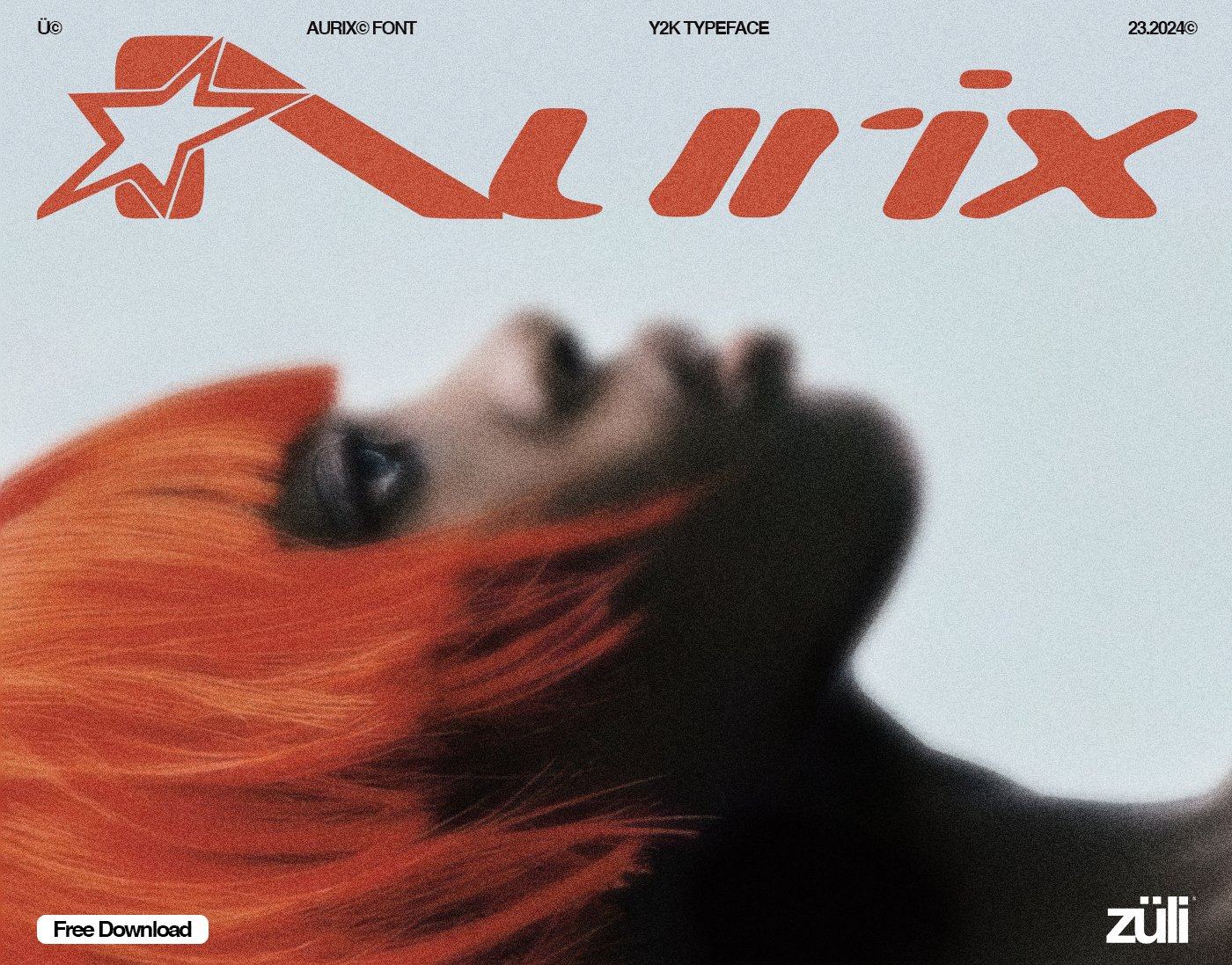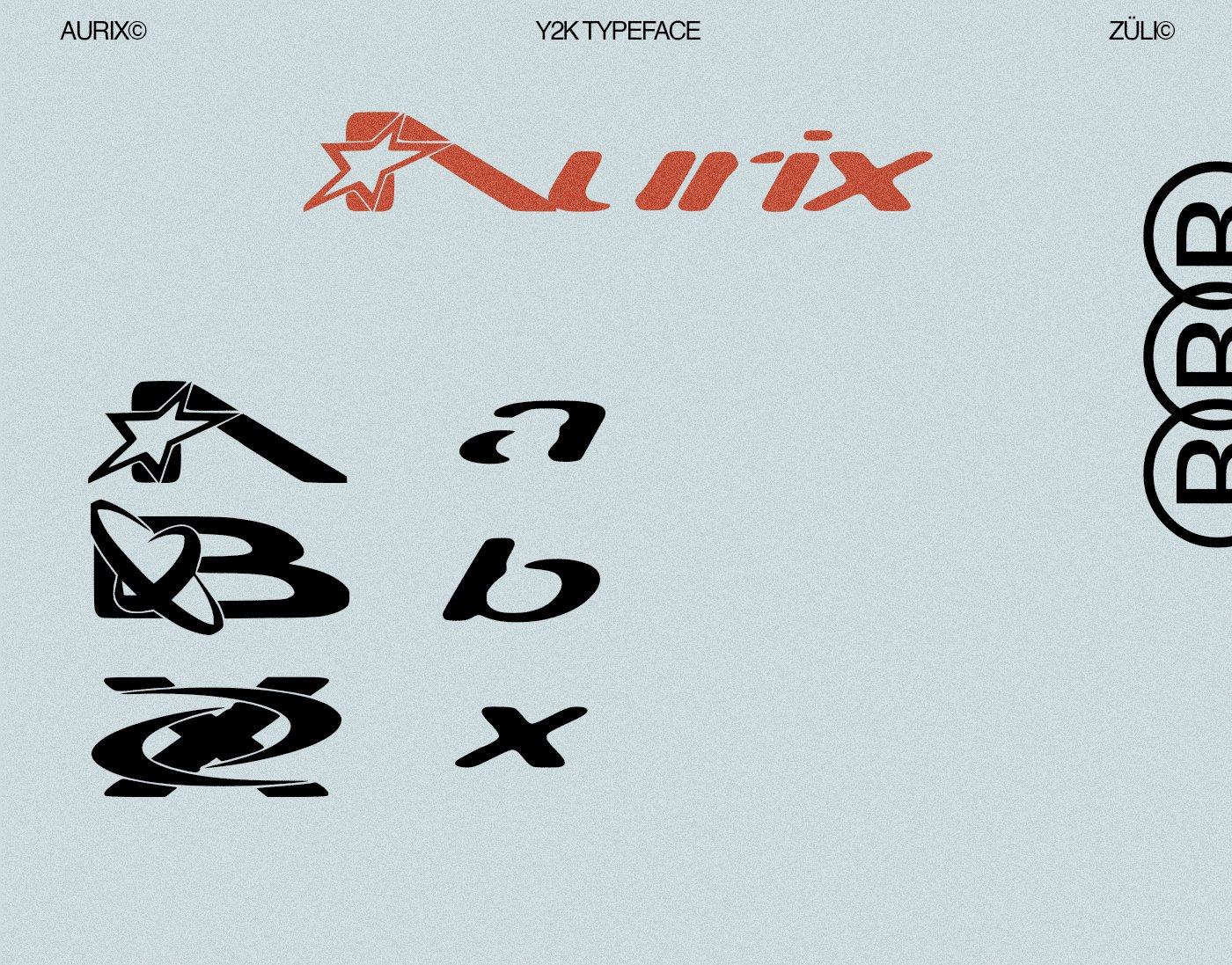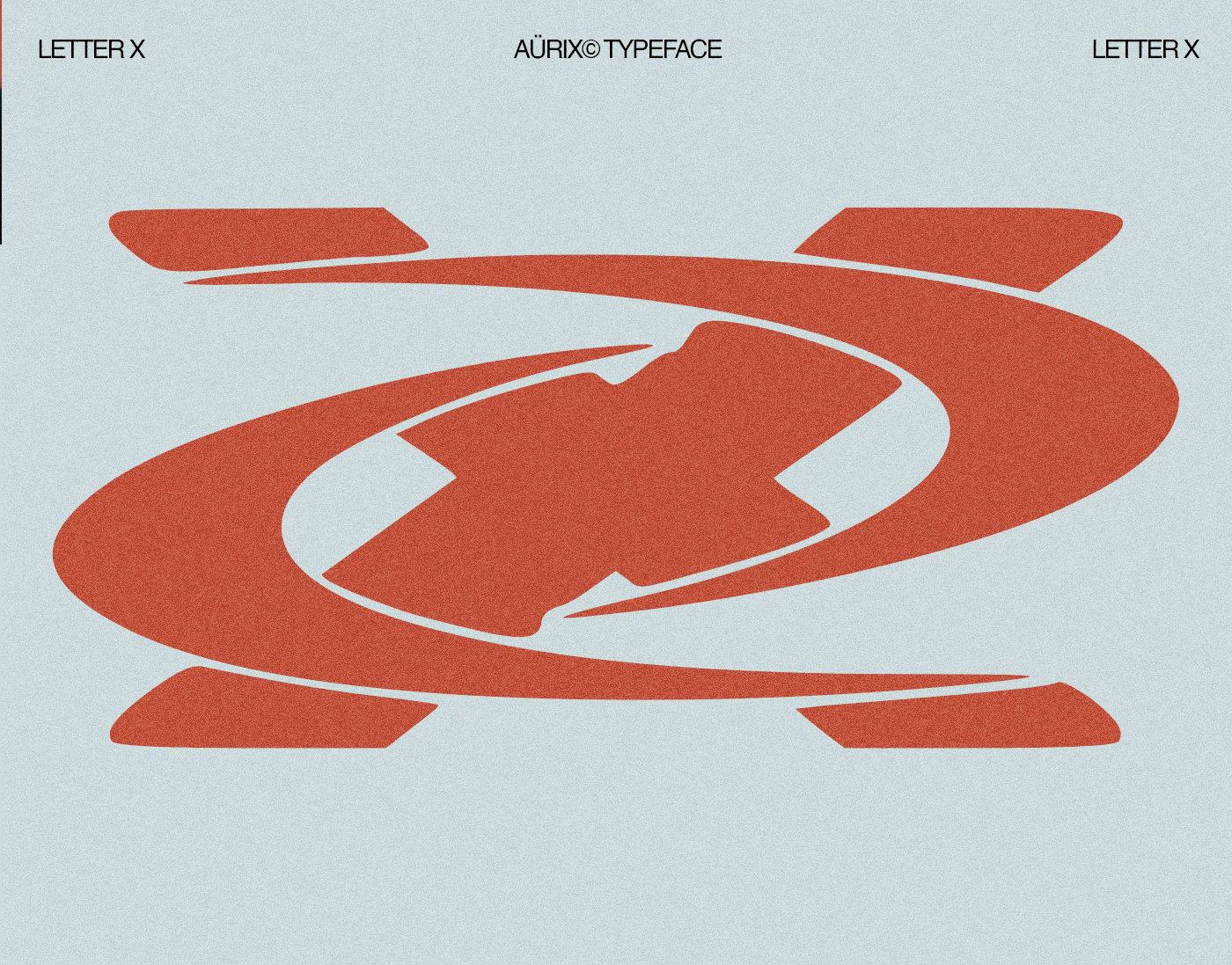
1. Giới Thiệu Aürix – Free Y2K Font
Bạn đang tìm kiếm một phông chữ mang đậm phong cách Y2K (Year 2000) để làm nổi bật thiết kế của mình? Aürix chính là lựa chọn hoàn hảo dành cho bạn! Với thiết kế độc đáo, các ký tự được lấy cảm hứng từ xu hướng thẩm mỹ retro tương lai những năm 2000, Aürix sẽ giúp bạn tạo ra những tác phẩm nghệ thuật đậm chất hoài cổ nhưng vẫn hiện đại.
2. Đặc Điểm Nổi Bật Của Aürix Font
✨ Phong Cách Y2K Độc Đáo:
- Thiết kế mang đậm dấu ấn thập niên 2000 với các yếu tố retro và tương lai kết hợp.
- Các chữ cái viết hoa (Capital Alphabets) đã được tối ưu hóa với hình dáng Y2K “sẵn sàng sử dụng”.
🎨 Phù Hợp Mọi Dự Án:
- Từ thiết kế áo quần, poster, bìa album đến các dự án kỹ thuật số như website, social media, Aürix đều dễ dàng hòa nhập và tạo điểm nhấn.
🎯 Thiết Kế Chuẩn Y2K:
- Các ký tự viết hoa được thiết kế đặc biệt với hình dáng Y2K, sẵn sàng để áp dụng vào mọi ý tưởng sáng tạo.
- Phong cách : Y2K (retro tương lai).
- Ký tự hỗ trợ : Capital Alphabets (Chữ in hoa).
5. Ứng Dụng Thực Tế
- Thời trang : Tạo họa tiết chữ độc đáo cho áo thun, hoodie, hoặc phụ kiện.
- Poster & Quảng cáo : Thêm phong cách Y2K vào chiến dịch marketing hoặc thiết kế poster.
- Bìa album & Nhạc số : Tái hiện phong cách âm nhạc những năm 2000.
- Social Media : Thiết kế story, post, hoặc reel với font chữ bắt mắt.